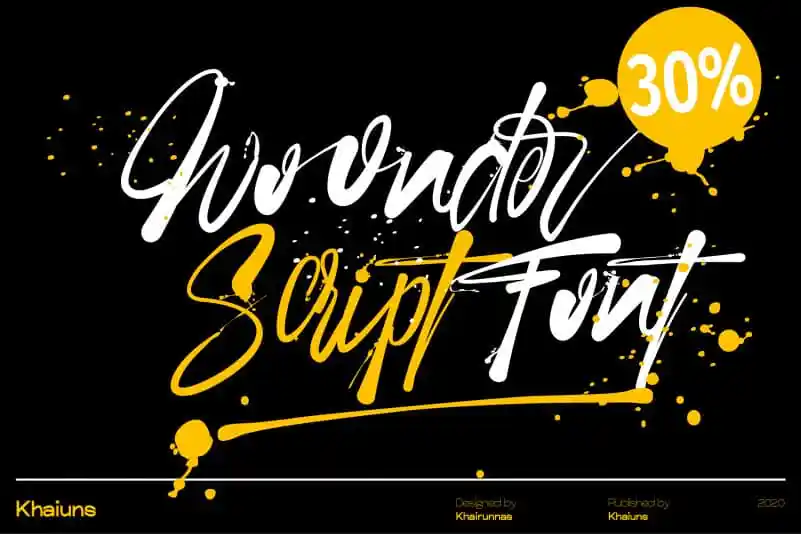
Woonder Script Font – Download Grátis
Woonder Script Fonts é uma elegante fonte brush que surgiu da mão do designer khaiuns, apresentando uma sensação vibrante e autêntica para quem quer enriquecer seus projetos com um touch único. Esta tipografia é perfeitamente concebida para ser personalizada conforme o seu gosto, contendo dois conjuntos de letras, que incluem swashes e texturas únicas. O designer oferece uma maneira fácil e interessante de encontrar uma fonte Woonder Script única: basta adicionar um plus (+) a cada letra e número para obter uma combinação interessante. A brilhante ideia da fonte, que permite personalização e originalidade, torna essa opção um verdadeiro favor aos profissionais de design gráfico. Experimentar Woonder Script Fonts é o primeiro passo rumo a uma experiência de criação mais criativa e inspiradora.